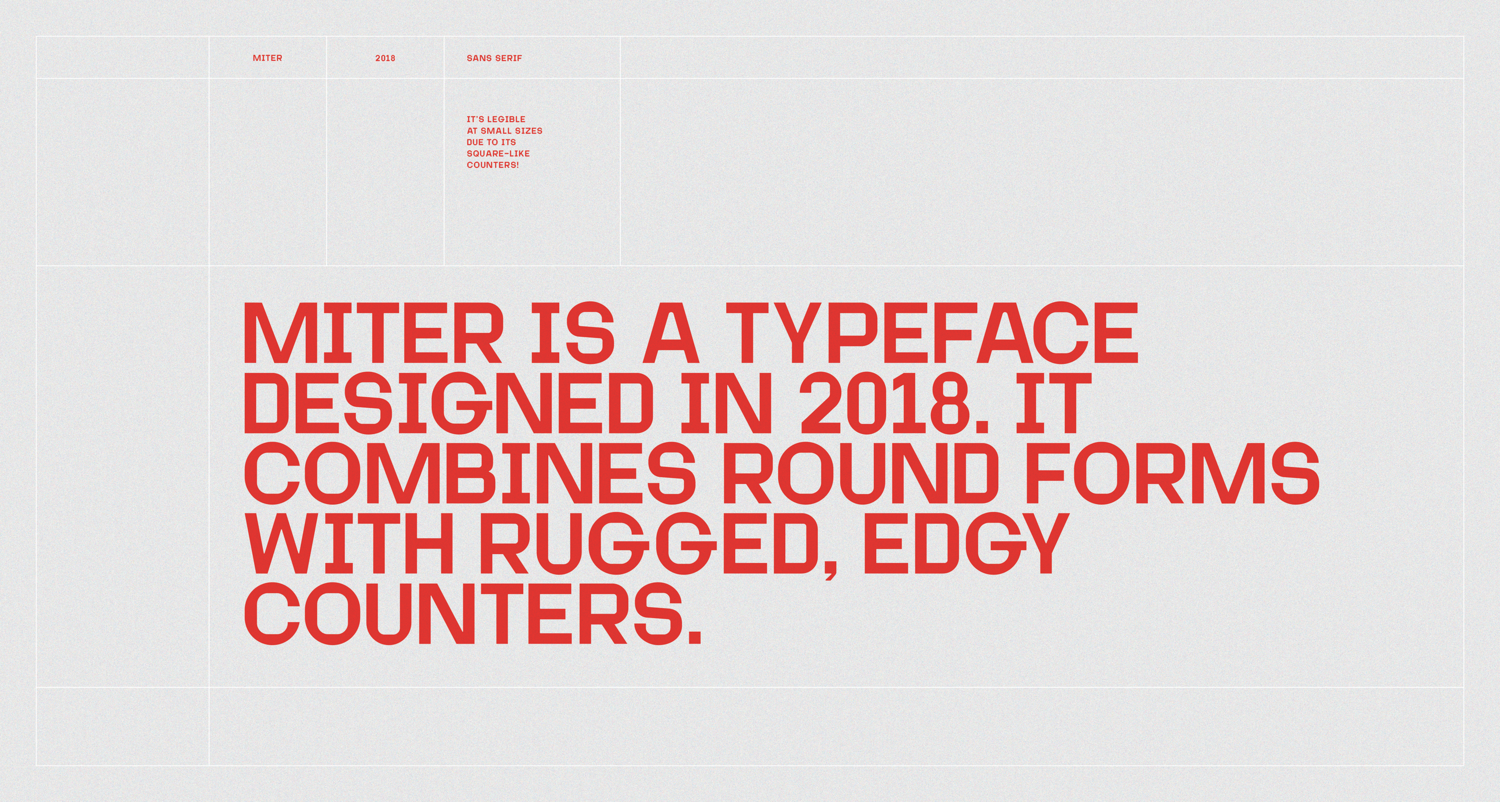
A Miter Typeface é uma elegante escolha para aqueles buscando um estilo Clean e moderno na sua identidade visual. Cada caractere desta fonte inspirada nas ferramentas industriais revela a graça que brota do equilíbrio perfeito das circunferências, fazendo dela uma opção inovadora não apenas para logomarcas e identidades de marca vintage, mas também para aplicações em cartazes e artigos. A Miter é um título face ideal para estilos modernos que valorizam a simplicidade da geometria, combinando perfeitamente com o design do século XXI. Seja você criador de arte digital ou designer gráfico tradicional, a Miter oferece uma maneira fresca e versátil de expressar seus trabalhos nas páginas dos jornais ou nos cartazes urbanos.